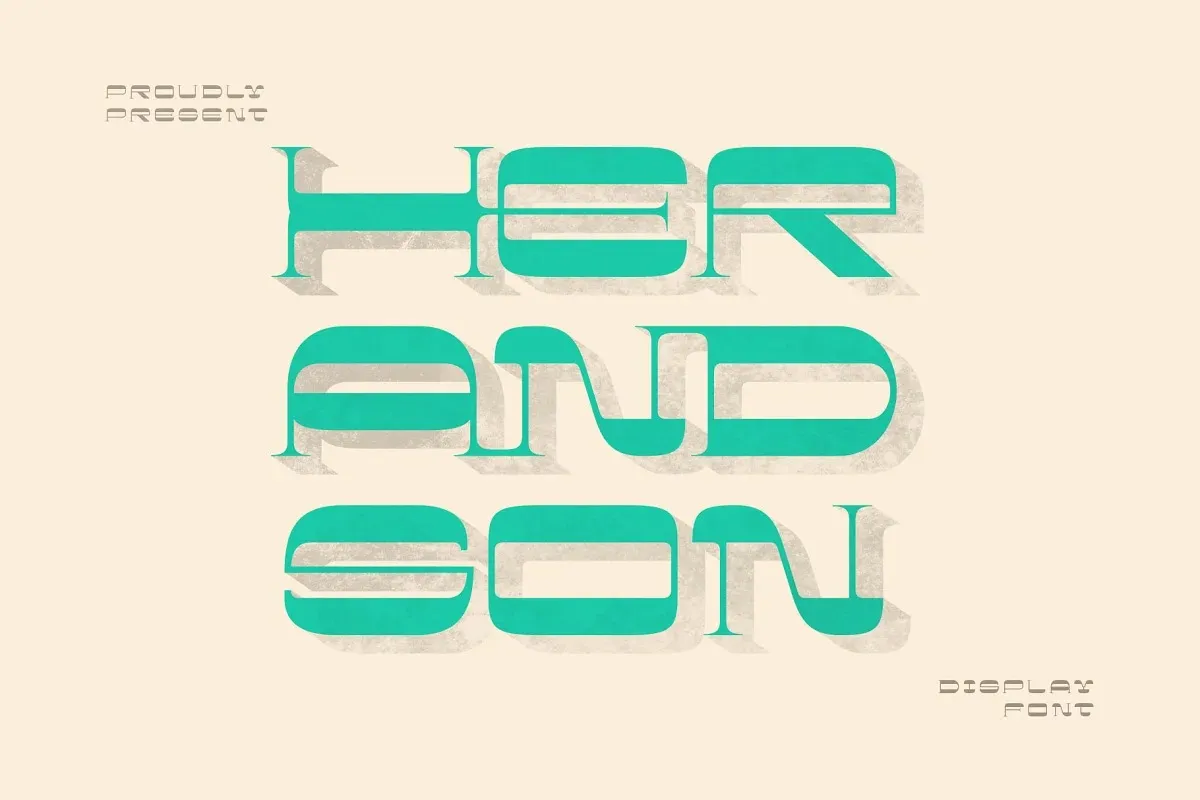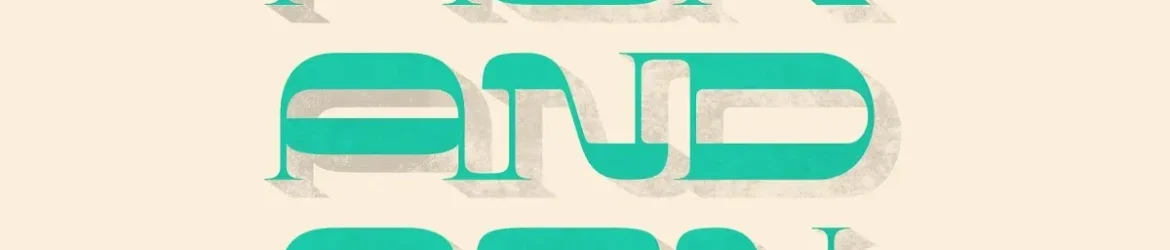
Esta fonte é ideal para ambientes descolados e sofisticados, perfeita para criar designs vintage com atração. Ela tem uma contraste invertido que oferece um tom revigorante às criações digitais, lembrando dos estilos de design da década de 1970. Inspirada no estilo retro das décadas passadas, essa fonte traz a essência de antiguidade e elegância sem ser séria demais. Suas linhas suaves e arredondadas fornecem um contraste atraente com qualquer tipo de texto ou design associado. A “Her and Son” também é uma fonte desafiadora, mas não para tanto que seja difícil lembrar-se dela. É como se ela tivesse sua própria personalidade única, tornando-a memorável e capaz de adicionar um toque especial a qualquer projeto visual. Com um design prático e elegante, a fonte é fácil de usar em projetos digitais ou impressos. Ela traz ao seu design uma personalidade vibrante que certamente chamará atenção. Se você está procurando por uma fonte reverso contrast com o charme da década de 70 e um toque atemporal, “Her and Son” é a escolha perfeita para tornar seus projetos digitais únicos e memoráveis.